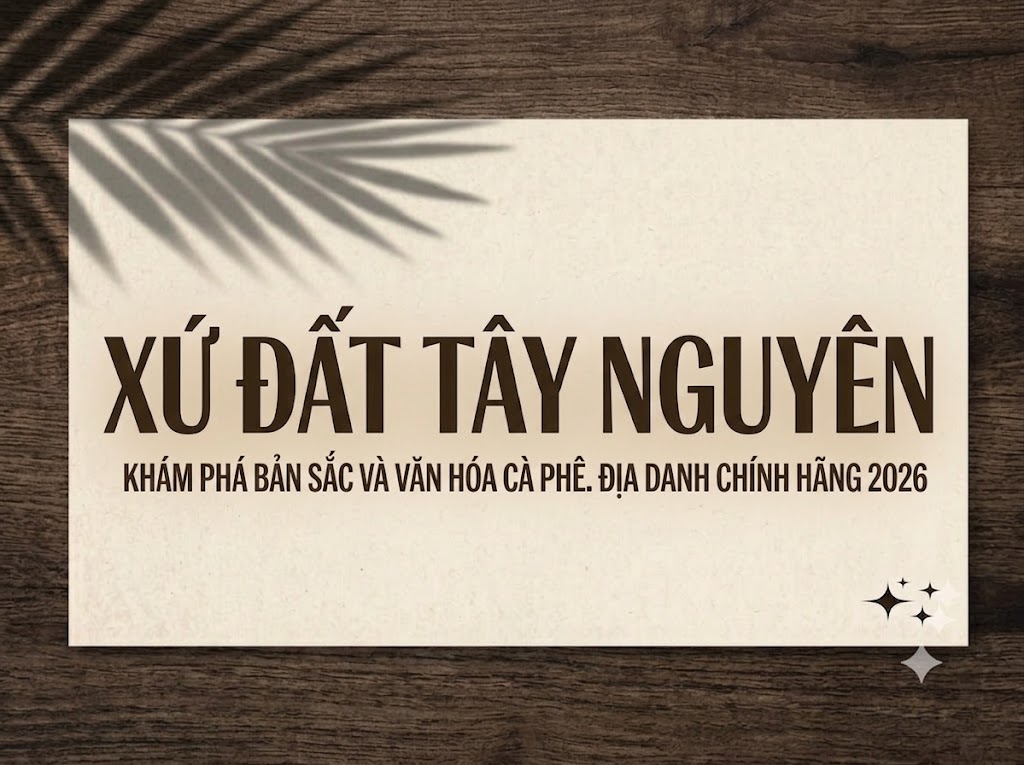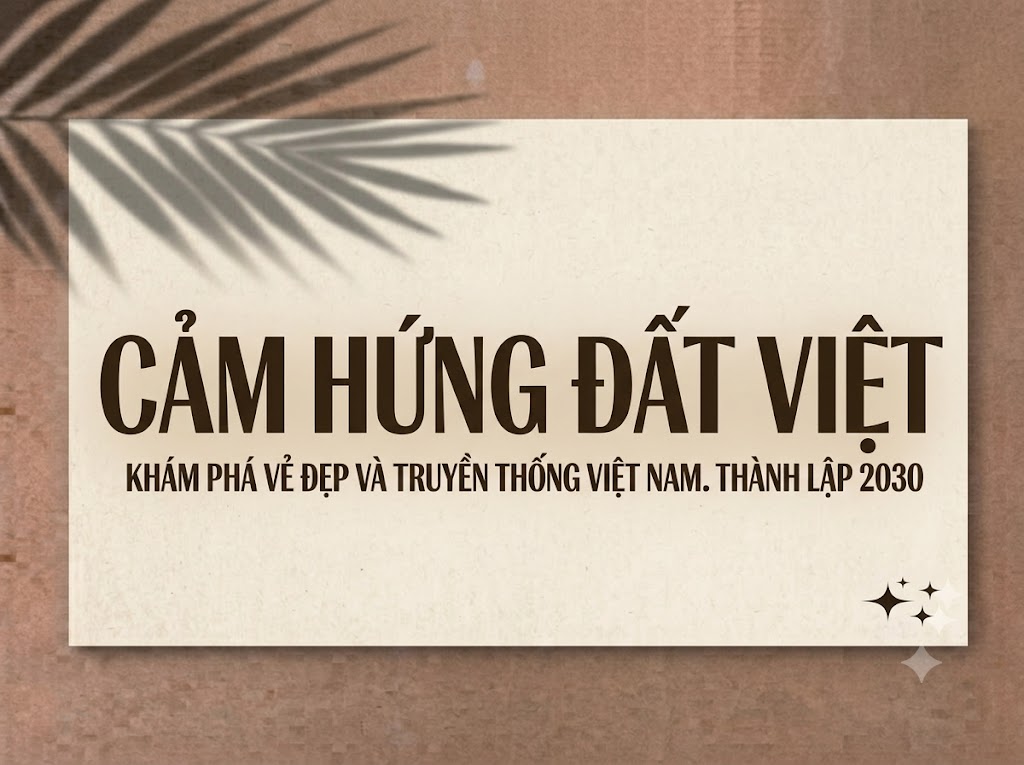
1FTV Crima
Trong nghệ thuật sắp đặt chữ (typography), có những bộ phông được sinh ra không chỉ để đọc, mà là để tạo ra bầu không khí và khơi gợi cảm xúc mạnh mẽ. Nếu những phông chữ tròn trịa mang lại cảm giác thân thiện, phông không chân mang lại sự tối giản, thì dòng chữ Serif gai góc với độ tương phản cực hạn luôn là chìa khóa mở ra thế giới của sự xa xỉ, ma mị và đầy tính nghệ thuật.
Nếu bạn đang tìm kiếm một vũ khí typographic độc bản, vừa mang hơi thở vương giả của trường phái cổ điển, vừa ẩn chứa nét nổi loạn, sắc sảo để làm bừng sáng các dự án thiết kế của mình, thì 1FTV Crima chính là một kiệt tác không thể bỏ qua.
Giới thiệu về font 1FTV Crima
Font 1FTV Crima là một bộ chữ hiển thị có chân (serif display) sở hữu phong cách thiết kế vô cùng táo bạo, pha trộn hoàn hảo giữa cấu trúc chữ Modern Serif thời thượng và tinh thần Gothic bí ẩn.
Những đặc điểm thiết kế “gây nghiện” của 1FTV Crima
Sức hút thị giác đầy mê hoặc của font 1FTV Crima đến từ sự tính toán kỹ lưỡng trong từng nét vẽ, tạo nên một tổng thể vừa uy nghiêm vừa phá cách:
Độ tương phản cực hạn (Extreme Contrast): Thừa hưởng nét đặc trưng của các dòng font luxury, Crima sở hữu những cột dọc (stems) siêu dày, đen đặc, đặt cạnh các đường liên kết ngang (hairlines) mỏng như sợi chỉ. Sự tương phản kịch tính này giúp chữ có chiều sâu và lập tức thu hút ánh nhìn.
Điểm nhấn ngôi sao/kim cương độc bản: Đây chính là chi tiết đắt giá nhất của bộ font này. Các dấu chấm trên chữ i, j hay các dấu câu như dấu chấm hỏi (?), dấu chấm than (!) không phải là hình tròn hay hình vuông thông thường, mà được cách điệu thành hình ngôi sao bốn cánh (hoặc hình kim cương vát nhọn) cực kỳ sắc sảo.
Chân chữ vạt nhọn sắc mảnh: Phần chân chữ (serif) được thiết kế dạng vát nhọn phẳng dẹt, sắc sảo như những chiếc gai hoặc lưỡi dao, giúp cân bằng lại sức nặng của các nét dọc dày dặn và tạo nên một kết cấu chữ vô cùng kiên định, mạnh mẽ.
Hình ảnh demo thực tế của font 1FTV Crima
Kích thước nhỏ (12pt – 24pt): Nhờ kết cấu hình khối đứng dáng và khoảng hở chữ được tính toán khoa học, các nét chữ viết thường và chữ số vẫn hiển thị vô cùng sắc nét, ngay ngắn, tạo trải nghiệm đọc rất tốt trên màn hình thiết bị di động.
Kích thước lớn (36pt – 72pt): Đây chính là không gian để 1FTV Crima tỏa sáng rực rỡ nhất. Các chi tiết ngôi sao bốn cánh trên chữ i, độ sắc lẹm của chân chữ và đường cong đầy kịch tính của các chữ cái như c, s, g hiện lên vô cùng lộng lẫy, tạo tác động thị giác cực mạnh cho dòng tiêu đề.
Ứng dụng thực tế trong thiết kế đồ họa và sản xuất video
Sở hữu nét cá tính đầy vương giả, ma mị và sắc sảo, font 1FTV Crima mở ra một không gian sáng tạo vô cùng rộng lớn cho các designer và nhà sáng tạo nội dung:
Tiêu đề mở đầu cho video ngắn (TikTok, Reels, Shorts): Với xu hướng xem video trên màn hình dọc tỷ lệ 9:16, một cụm chữ tiêu đề giật tít sử dụng 1FTV Crima ở phần intro sẽ giữ chân người xem lướt chậm lại ngay lập tức.
Thiết kế ảnh thu nhỏ YouTube (Thumbnail) đầy tính nghệ thuật: Giúp các video nhạc lofi, acoustic, các nội dung chia sẻ kiến thức chuyên sâu hoặc phim ngắn indie bứt phá tỷ lệ nhấp chuột (CTR) nhờ phần nhìn vô cùng chuyên nghiệp và khác biệt so với các dòng font đậm thông thường.
Nhận diện thương hiệu phân khúc Luxury & Streetwear: Rất thích hợp làm logo dạng chữ khối, biểu ngữ quảng cáo, menu các nhà hàng/quán bar mang phong cách cổ điển.